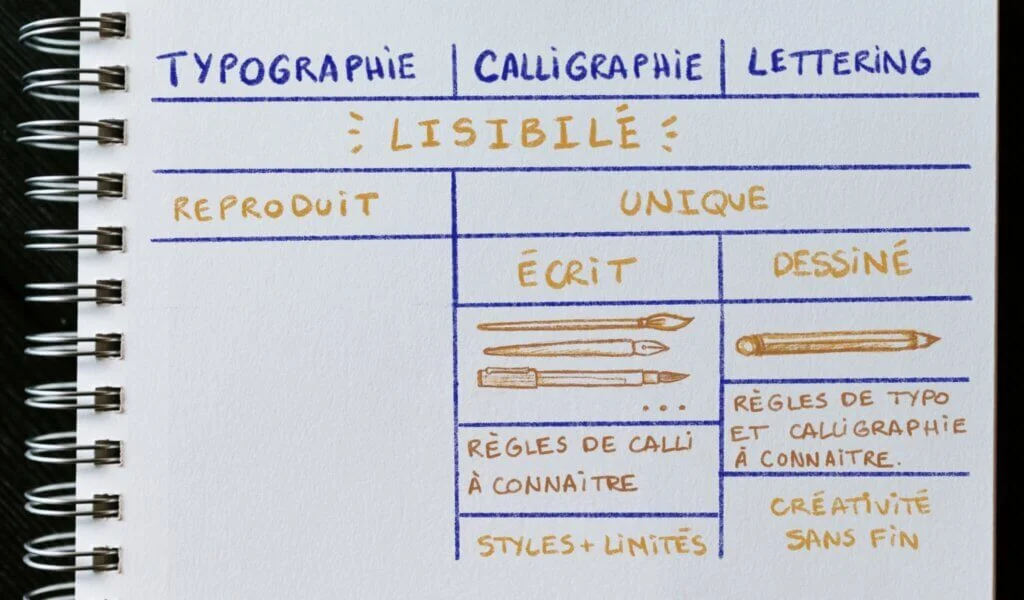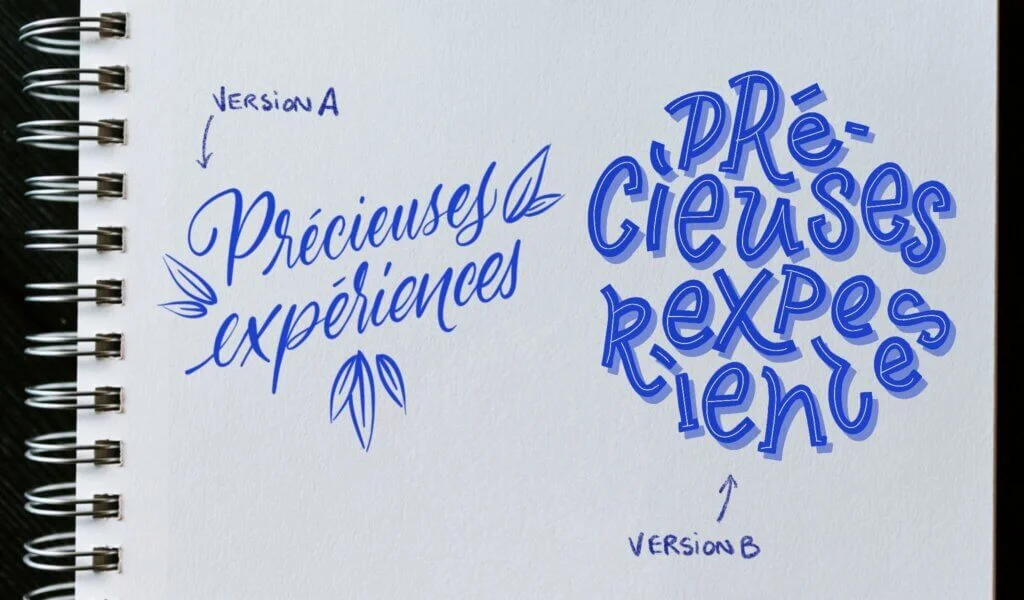
Lettering, calligraphie, typographie, brush lettering… On s’y perd ! Même moi, quand j’ai commencé, c’était un peu le bazar dans mon esprit entre toutes ces techniques. Les artistes utilisent parfois les mêmes termes… Pour des visuels totalement différents ! Comment réussir à distinguer le lettering de la calligraphie ? Et le brush lettering, c’est du lettering tout court ? Depuis mes débuts, j’ai expérimenté, pratiqué et appris. Aujourd’hui, je suis même formatrice en lettering. Alors, j’ai décidé de te partager mes connaissances pour t’aider à faire la différence entre calligraphie, lettering et typographie.
Pas que !
Oui, un point commun de ces trois spécialités artistiques, c’est qu’elles ont un but esthétique. On va créer de belles lettres, dans tous les cas.
Mais leur ultime dénominateur commun, c’est leur lisibilité.
Calligraphie, lettering ou typographie : les lettres et les mots doivent pouvoir être lus.
L’idée, c’est vraiment de pouvoir faire passer un message compréhensible. Pour cela, les personnes doivent pouvoir déchiffrer les lettres, sans peine.
Sinon, on tombe dans le côté purement artistique et c’est une nouvelle spécialité artistique.
Pour te simplifier la vie, j’ai créé ce tableau pour t’expliquer la différence entre calligraphie et lettering ou encore la typographie.
Et maintenant, suis-moi : je vais t’expliquer tout ça.
La typographie se distingue immédiatement de la calligraphie et du lettering parce qu’elle a pour but d’être reproduite.
On parle de polices de caractères ou de fonts.
Les typographes imaginent un ensemble, un alphabet complet avec les graisses, les pattes, les terminaisons, les virgules et les chiffres qui sont dédiés à être reproduit de manière uniforme et identique.
La police de caractère dans laquelle j’écris cet article en est un exemple. Prends un livre sur ton étagère, ouvre une page : le titre est dans une font particulière, le corps de texte dans une autre.
Ces polices ont été créées dans le but d’être lisibles et reproduites.
C’est un travail spécifique, qui demande de la patience et de la minutie ainsi qu’une bonne dose de compréhension des pratiques de lecture.
Eh oui : on n’utilise pas la même police de caractères en ligne que sur papier, dans un souci de confort de lecture. Il y a aussi des enjeux d’accessibilité où les typographes créent des polices pensées pour les personnes dyslexiques, par exemple.
La calligraphie signifie littéralement l’art de la belle écriture, si on s’en réfère à son origine étymologique.
La calligraphie et le lettering se distinguent de la typographie parce qu’elles sont uniques et réalisées à la main.
L’idée n’est pas de reproduire les lettres ou les mots, mais vraiment de créer un travail unique, avec des aspérités et des imperfections.
On ressent le savoir-faire et le fait main dans la calligraphie et le lettering. C’est d’ailleurs ce que nos clients viennent chercher.
Alors qu’est-ce qui différencie la calligraphie et le lettering ?
La calligraphie, c’est le fait de ne presque pas lever le crayon : on va écrire le mot en une fois, peu importe l’outil utilisé.
Un peu comme quand tu écris, finalement.
En calligraphie, on utilise pas mal d’outils :
Et aussi, des styles uniques aux règles précises, parmi elles :
Je regroupe le brush lettering dans la calligraphie.
Comme son nom l’indique, tu vas utiliser un brush pen. À partir du moment où tu utilises cet outil, tu vas écrire ton mot presque en une seule fois.
Du coup, pour moi, ça rentre dans la catégorie de la calligraphie.
Aaaah, le lettering !
Je réalise des vitrines en lettering pour ma clientèle.
Le but ? Réaliser un lettrage qui attire l’attention.
Le lettering, c’est dessiner, là où la calligraphie, c’est écrire.
Le lettering, aussi nommé handlettering, c’est l’art de dessiner les lettres.
Contrairement à la calligraphie, où se côtoient des règles et des styles précis, le lettering laisse place à la créativité de l’artiste.
Le lettering, c’est de l’illustration de mots, de lettres… Donc, le champ des possibles est immense !
si tu as une question, ça sera un plaisir d’y répondre. Tu peux me laisser un commentaire ou me la poser directement sur Instagram.Comme, j’aime le rappeler à mes élèves : l’imagination est la seule limite.
En termes d’outils, un simple crayon à papier ou juste le stylet de la tablette graphique suffit.
Quand je réalise un lettrage (traduction de lettering) je procède exactement comme une illustration : recherche au crayon d’un style de typographie que j’aime, je recherche une composition, j’affine mes traits, je mets au propre et je fini par la mise en couleurs. Chaque lettrage est vraiment unique.
Je ne te cache pas qu’avoir des bases de calligraphie, de typographie et de composition pour réaliser des letterings avec un vrai impact et qui soient agréables à l’œil, ça aide.
Heureusement, on peut apprendre toute sa vie et Internet regorge de ressources : le savoir est à portée de main !
As-tu compris toutes les nuances de l’art subtil des belles lettres ?
Jouons un peu !
Fais-tu la différence entre calligraphie et lettering dans cette image ?
J’espère que cet article t’aura permis d’y voir plus clair et de distinguer la différence entre calligraphie et lettering… et la typographie. L’art des lettres, c’est un univers riche où il y a matière à s’amuser… et développer dans notre créativité. Ça te donne envie d’essayer ?